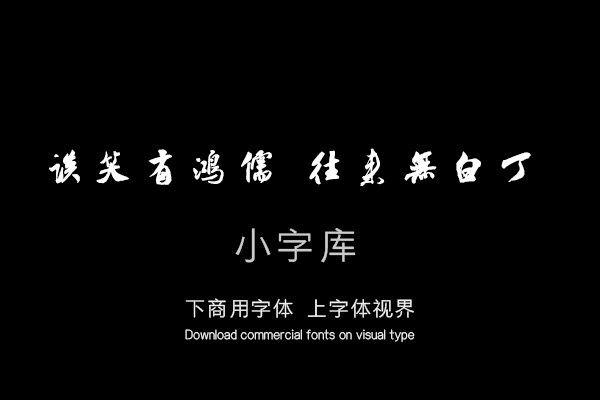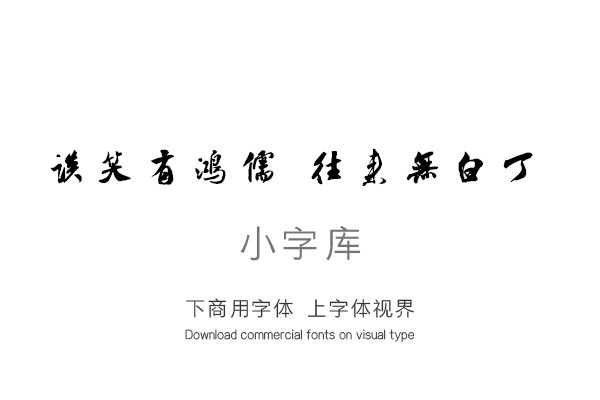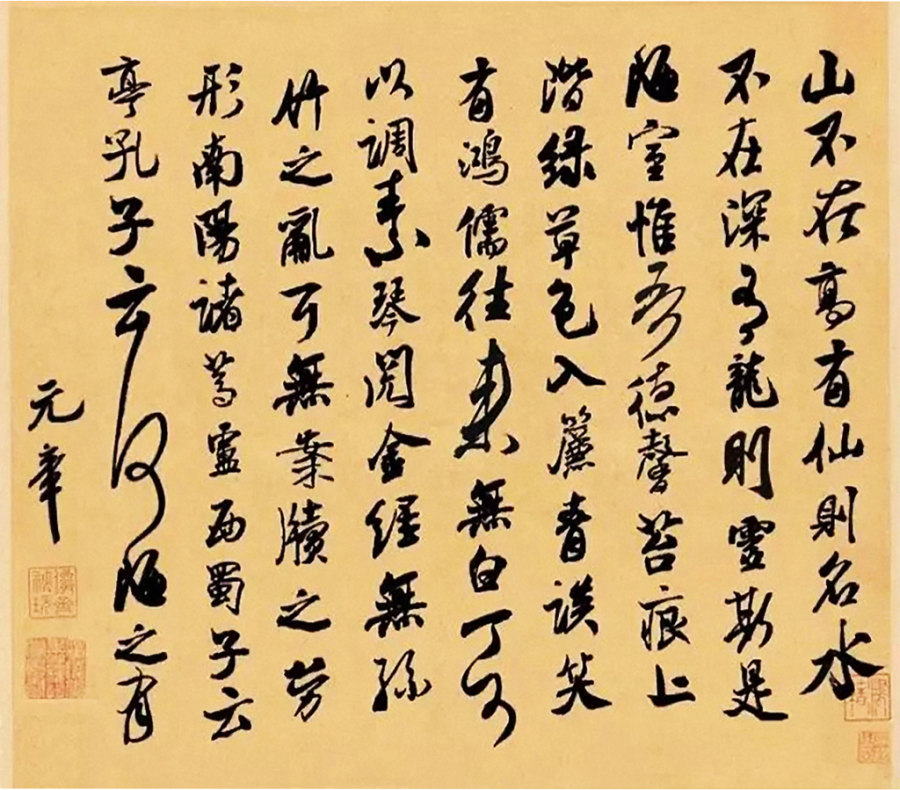
《汉标米芾集字陋室铭》 小字库是由“汉标字库”耗时2年,收集古代知名书法家真迹制作而成,例如:《汉标米芾集字陋室铭》 字库是基于北宋米芾经典书法作品集字《陋室铭......单字授权
山不在高,有仙则名。水不在深,有龙则灵。斯是陋室,惟吾德馨。苔痕上阶绿,草色入帘青。谈笑有鸿儒,往来无白丁。可以调素琴,阅金经。无丝竹之乱耳,无案牍之劳形。南阳诸葛庐,西蜀子云亭。孔子云:何陋之有?元章。